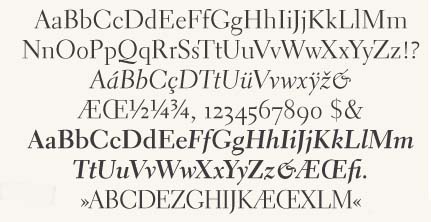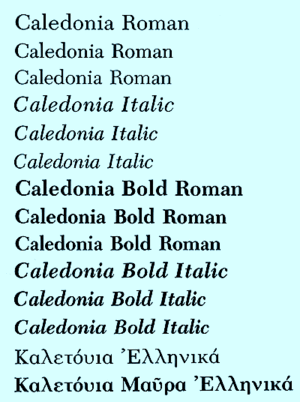
William Addison Dwiggins (1880-1956)
Tipógrafo norte-americano, que cunhou o termo «graphic designer». Autor de fontes como a Electra e a Metro.William Addison Dwiggins foi artista gráfico, ilustrador e desenhador de tipos norte-americano. William Addison Dwiggins foi designer de livros, calígrafo, ilustrador e tipógrafo. Nasceu em Martinsville, Ohio. Dwiggins foi aluno no curso de lettering de Frederic W. Goudy na Frank Holme Schools of Illustration, em Chicago. Fontes"The essence of type design is to hit middle ground between mechanical exactitude and the flow and variety of a written hand." (1941). Dwiggins criou os tipos
A «letra económica»Como lograr uma letra condensada satisfatória, legível? A princípios de 1942, durante a época de restrições económicas impostas pela II. Guerra Mundial, W.A. Dwiggins começou uma série de testes, buscando uma tipografia altamente económica; ao mesmo tempo, solicitaram-lhe uma tipografia com um certo aire espanhol. Os dois projectos confluíram num só e o resultado foi a fonte Eldorado, lançada em New York pela Mergenthaler Linotype Company em 1953. Para Dwiggins, a ideia duma letra económica não era nada de novo, mas neste caso centrou a sua atenção em atingir a economia de espaço através de formas condensadas dos caracteres, em vez se fixar no ajuste vertical comum nos tipos usados para jornais e periódicos. Embora nunca alcançasse muita popularidade, a Eldorado ilustra alguns conceitos básicos para desenhos de letra tendo a economia de espaço como sua principal característica. O grande perigo que existe no desenho de tipografias condensadas é querer comprimir tudo e todas as letras. Dwiggins elegeu cuidadosamente as letras a comprimir: as letras que, pelas suas características, respondem mais positivamente a esta técnica. Comprimiu a, f, r, s e t ao limite máximo, sem perder- lhes as suas características distintivas (note-se a contundente forma do a e o ombro agudo da f); as letras com contraformas cerradas (b, d, g, o, p, q) gozam de um espaço interior generoso; as letras com traços diagonais (v, w, x, y) obtiveram ângulos mais cerrados que o normal. Todas estas características conjugadas, criaram uma fonte agradável, bem legível e sem mostrar uma compressão demasiado óbvia. A ElectraLançada no mercado tipográfico em 1935, a fonte Electra de Dwiggins é uma das mais marcantes reinterpretações da tipografia classicista, fabricada expressamente para as máquinas Linotype. A inspiração veio de Pierre Simon Fournier, mas Dwiggins deu às letras do mestre francês uma «limagem» yankee. Pouco depois da Electra, foi introduzida no mercado em 1939/1940 a Fairfield de Rudolf Ruicka (um amigo de Dwiggins), também para a Linotype. Ambas as fontes, não muito diferentes, foram durante cerca de 40 anos (!) profusamente usadas para a composição de texto corrido nos EUA por exemplo, em revistas.
A fonte digital dispõe dos estilos Regular, Display, Cursive, Bold e Cursive Bold. Os desenhos originais de Dwiggins estão patentes na Boston Public Library. A Electra apareceu com uma romana inclinada a fazer de cursiva, mas foi o próprio Dwiggins que acabou por desenhar em 1940 o corte itálico hoje comum. http://www.smith.edu/libraries/libs PublicaçõesW.A. Dwiggins. WAD to RR, a letter about designing type. Cambridge. Harvard College Library, Cambridge, 1940 BibliografiaHeitlinger, Paulo. Tipografia: origens, formas e uso das letras. Copyright © 2006 Paulo Heitlinger, ISBN 10 972-576-396-3 , ISBN 13 978-972-576-396-4, Depósito legal 248 958/06. Dinalivro. Lisboa, 2006. Blumenthal, Joseph. The Printed Book in America. London. The Scolar Press Limited, 1977. p. 88. Carter, Sebastian, 'William Addison Dwiggins' in Twentieth Century type designers. London. Lund Humphries. 1995. p. 67. Tracy, Walter. The Typographic Scene. London. Gordon Fraser Limited. 1988. p. 30. McGrew, Mac. American Metal Typefaces of the Twentieth Century. Delaware. Oak Knoll. 1993. p. 168. Lawson, Alexander, Anatomy of a Typeface. Boston: David R. Godine, Publisher, Inc. 1990. p. 331. Shaw, Paul. Tradition and Innovation: 'The Design Work of William Addison Dwiggins' in Design Issues, Vol. I, No. 2 Mergenthaler Linotype Company, Falcon typeface specimen. New York: Mergenthaler Linotype Company, c. 1961. Fournier, Simon-Pierre le jeune, Modeles de Caracteres. Paris, 1742. Linotype and Machinery Limited, Caladonia type specimen. London : Linotype and Machinery Limited, c. 1953. Dwiggins, William Addison, WAD to RR a letter about designing type. Cambridge, MA, Harvard College Library, 1940. Merganthaler Linotype Company, Falcon type specimen. New York: Merganthaler Linotype Company. c. 1961. Dwiggins, William Addison, Eldorado type specimen. New York: Merganthaler Linotype Company, 1953. Thomas, Henry. Typography of the Spanish XVI century. London, Ernest Benn Ltd, 1926. McGrew, Mac, American Metal Typefaces of the Twentieth Century. Delaware: Oak Knoll, 1993. Shaw, Paul. Tradition and Innovation: 'The Design Work of William Addison Dwiggins' in Design Issues, Vol. I, Nº Tracy, Walter, Letters of Credit. London: Gordon Fraser Limited, 1986. Tracy, Walter, The Typographic Scene. London: Gordon Fraser Limited, 1988. Página actualizada em 09.2007 |